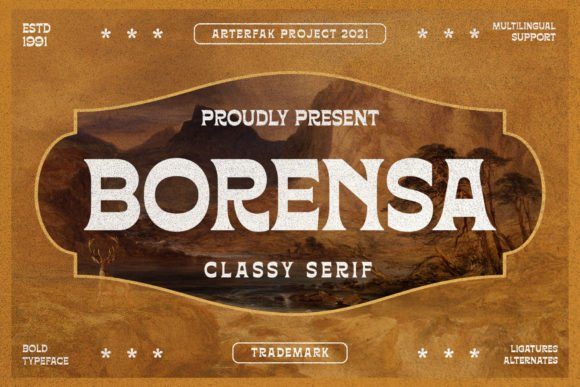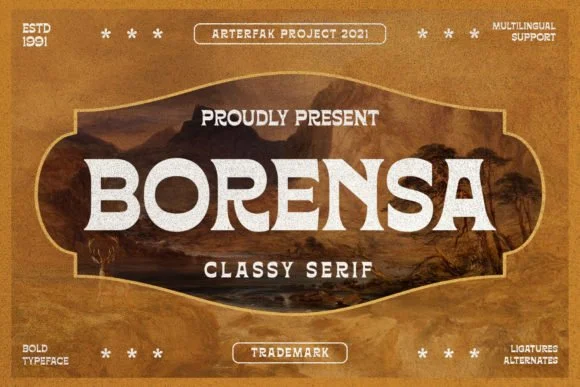
Название: Borensa Font (2021)
Borensa - это толстый шрифт, смелый и ретро-стиль.
Этот шрифт имеет внушительные размеры и уникальную форму букв, поэтому он легко подойдет для широкого спектра работ, требующих особого стиля.